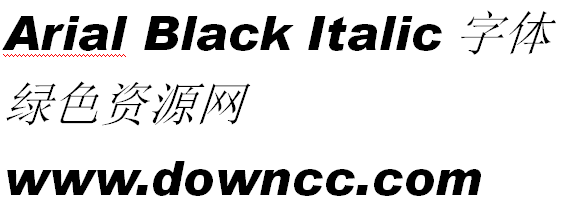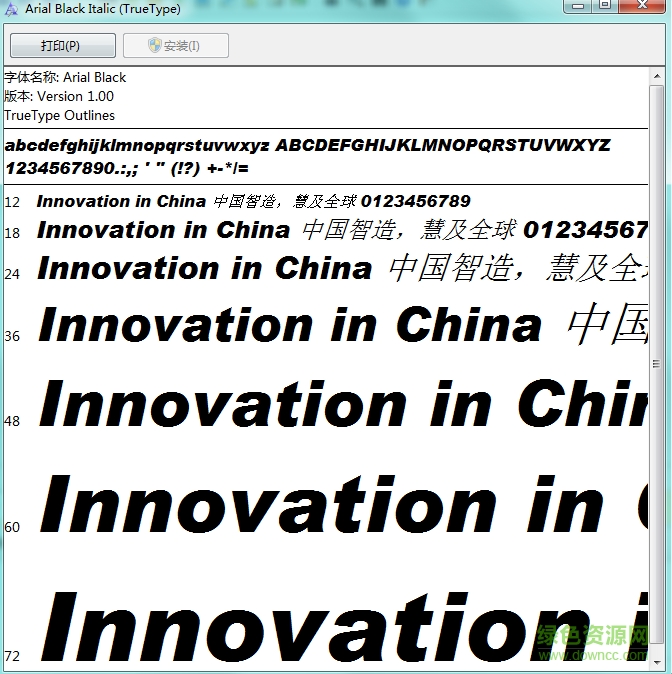
arial blackitalic是arial black系列的常規(guī)英文字體,有著簡明加粗的風格,字體微斜符合英文斜體規(guī)則,讓人眼目一新,如果你喜歡,來綠色資源網即可免費下載使用!
arial black italic翻譯為:黑體斜體,是arial字體中加黑傾斜的辯題,有著簡潔大方的書寫風格,可廣泛適用于平面設計、廣告創(chuàng)意、文字書寫等諸多方面。
意大利體起源于手寫體,16世紀初在意大利威尼斯就已經出現為節(jié)省版面的斜體。由于起源于手寫體,字形向右傾斜是其最大特征。最初是與正文完全不同的獨立字體出現的,現在電腦字體中已經作為在襯線體字體的一部分收入,在正體排版中需要強調、區(qū)別的時候使用。